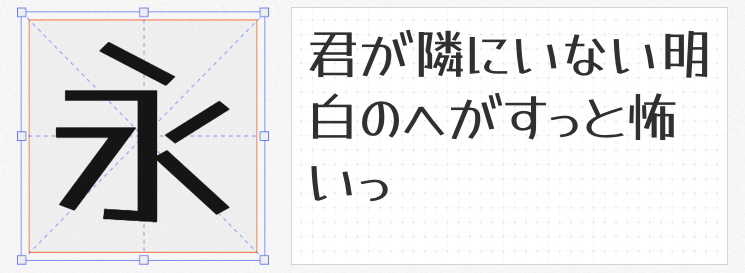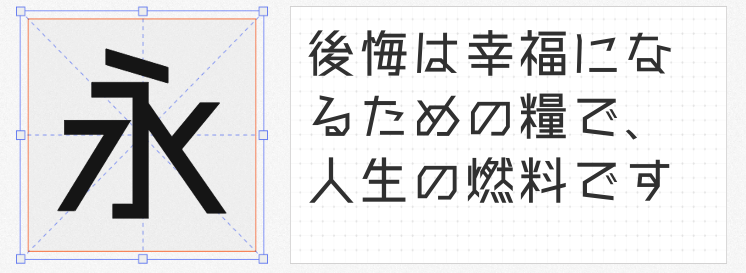
在日系设计风格盛行的当下,选择一款兼具个性与实用性的免费商用字体至关重要。本文精选四款风格鲜明的日文字体,涵盖手绘童趣、锐利科技感、可爱装饰性及马克笔质感,助力设计师高效完成作品且规避版权风险。
这款字体以“适当的哑光褪色”为特色,模拟手绘明朝体的自然笔触,笔画粗细过渡柔和,末端保留轻微毛边效果,营造出复古印刷品的质感。其字符集覆盖JIS第一水准2965个汉字,支持平假名、片假名、数字及标点符号,可广泛应用于包装设计、书籍标题、手作品牌视觉等场景。
由日本设计师打造的猫猫朋友体,将“口”部替换为心形图案,笔画拐角全部圆润化,彻底消除锋利感,整体风格天真活泼。该字体包含JIS第二水准6355个汉字及IBM扩展字符,总字符数近7000个,繁体字覆盖较全,简体缺失部分可用繁体替代。其应用场景包括儿童产品包装、社交媒体图文、女性品牌LOGO等。
这款字体以“圆珠笔用力书写”为灵感,笔画横平竖直,转折处呈现尖锐的直角,模拟数码转换过程中手写情感的流失感,形成独特的机械美学。它对繁体中文支持较好,简体中文缺字较多,适合科技产品海报、游戏界面、工业设计等场景。
基于马克笔手绘体更新优化,笔画起笔收笔为平直切角,转折处保留尖锐感,同时简化笔画弧度以提升可读性。该字体收录超7000个字符,支持JIS第二水准汉字,适用于儿童绘本、手账素材、轻食品牌包装等场景。